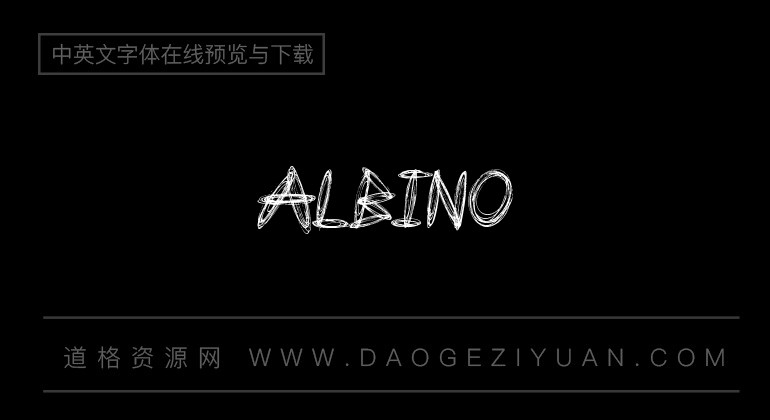
Albino
Albino字体是一种英文字体,它采用了细节丰富的英文字体设计,让文本更加清晰易读。它的字体设计风格具有传统感,但又不失现代感。Albino字体的字体细节可以让文字看起来更有深度,而且它的英文字母的笔画很漂亮,可以让文本看起来更加精致。Albino字体适用于文字排版和印刷,可以让你的文字看起来更加漂亮。
Albino是一款非常不错的手写艺术字体,具有很好的视觉感,适合于文化类的宣传设计、商业类品牌的广告和产品包装设计以及个性化文字排版等较多场景。